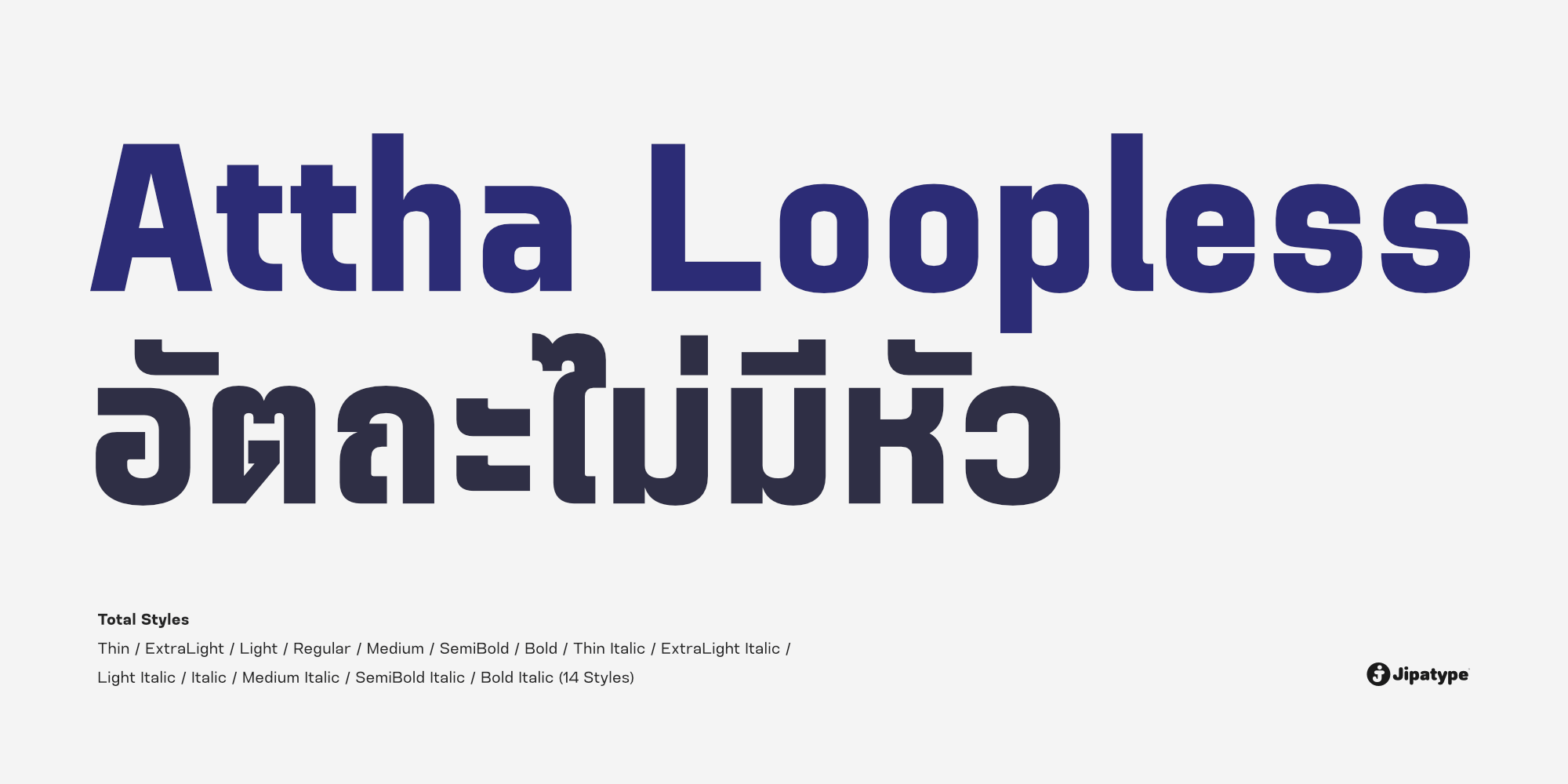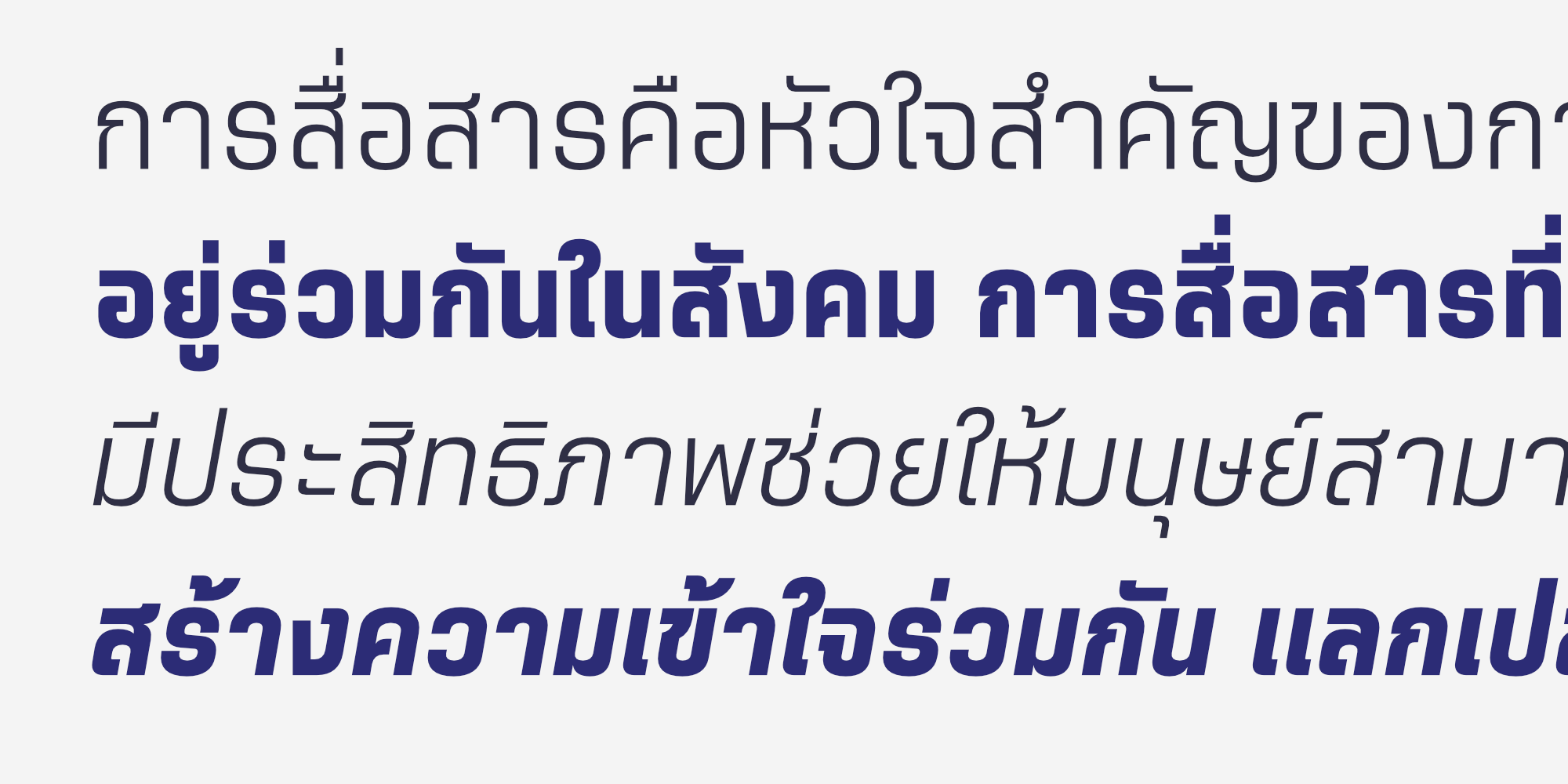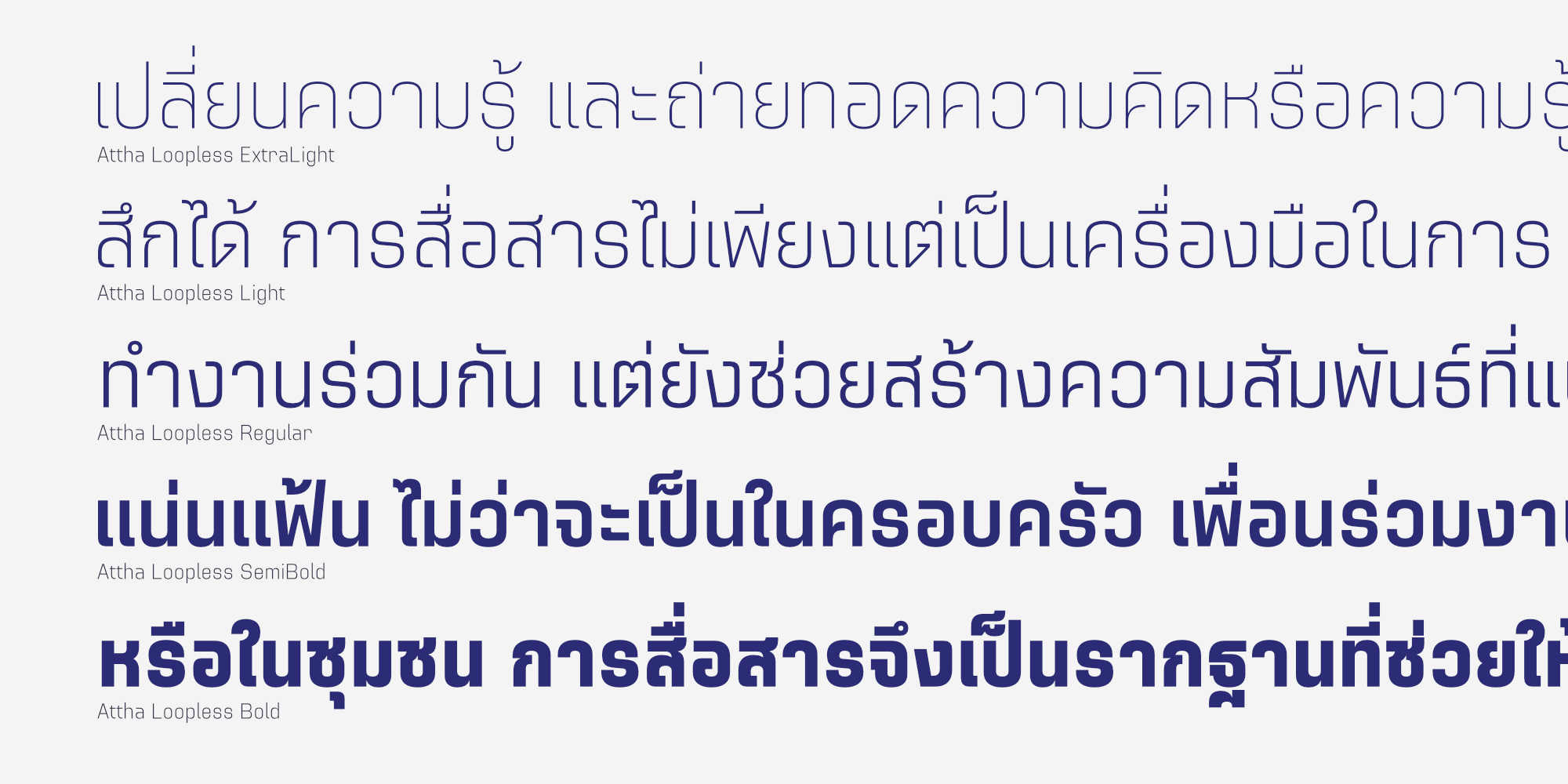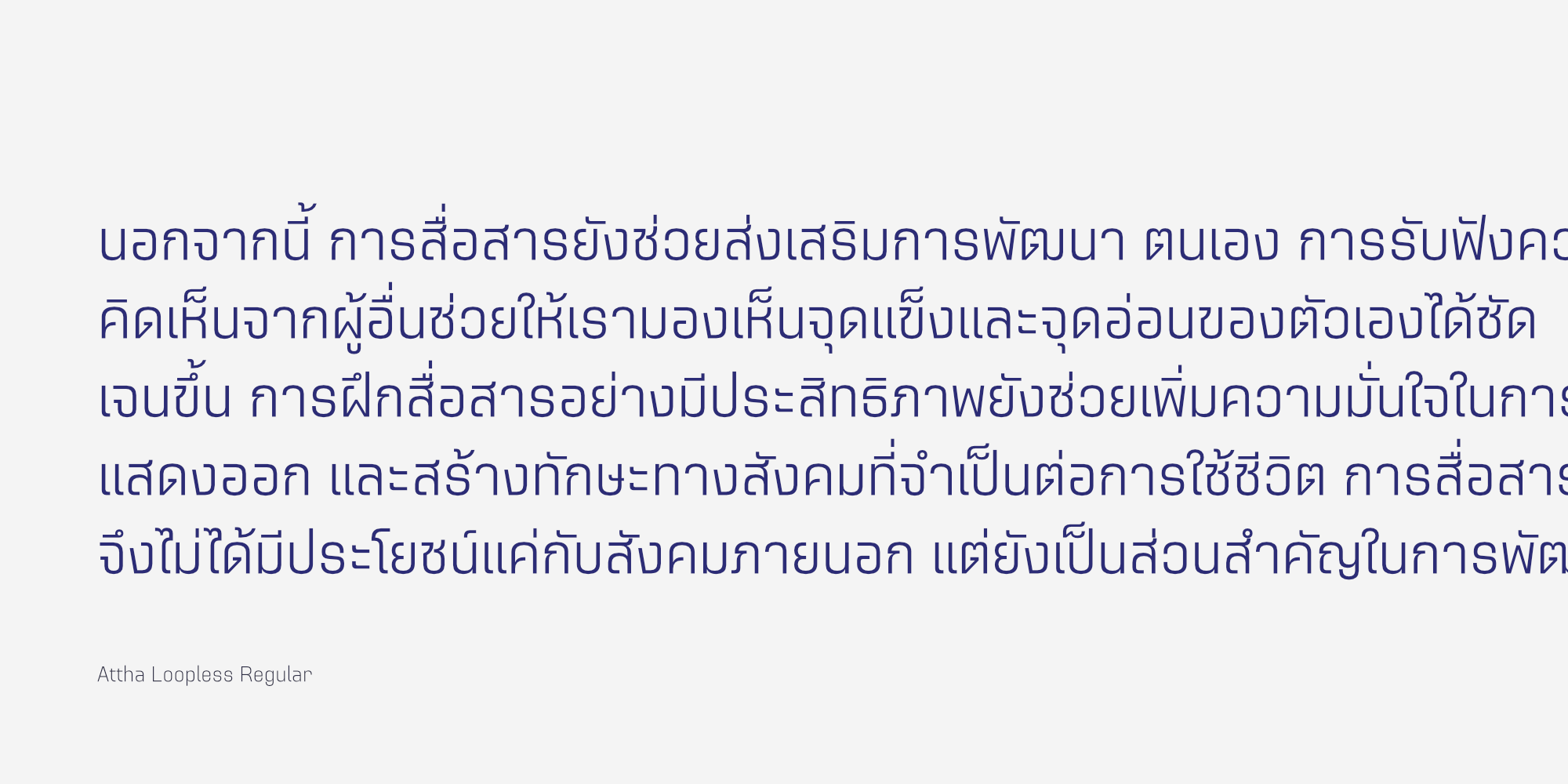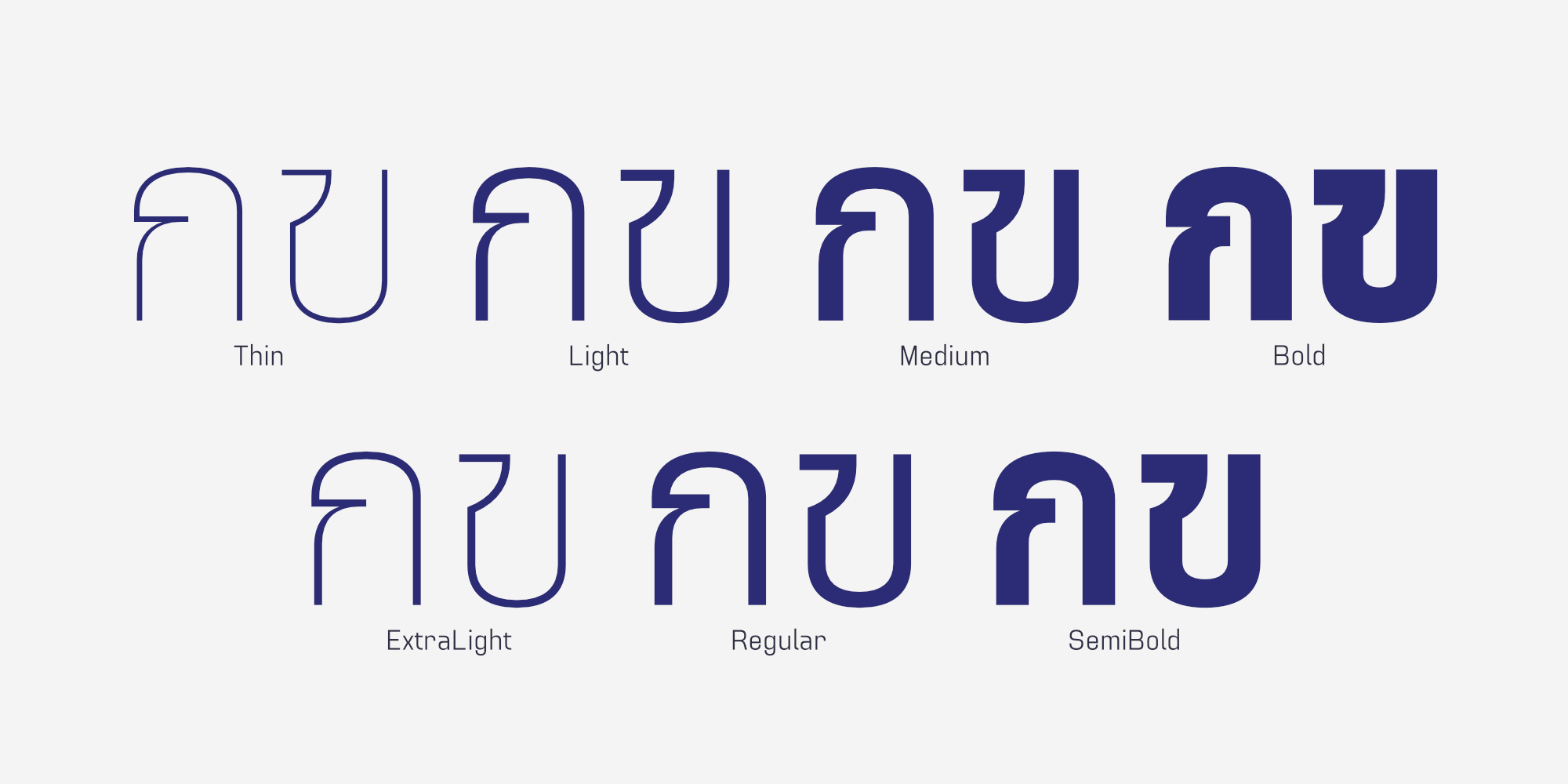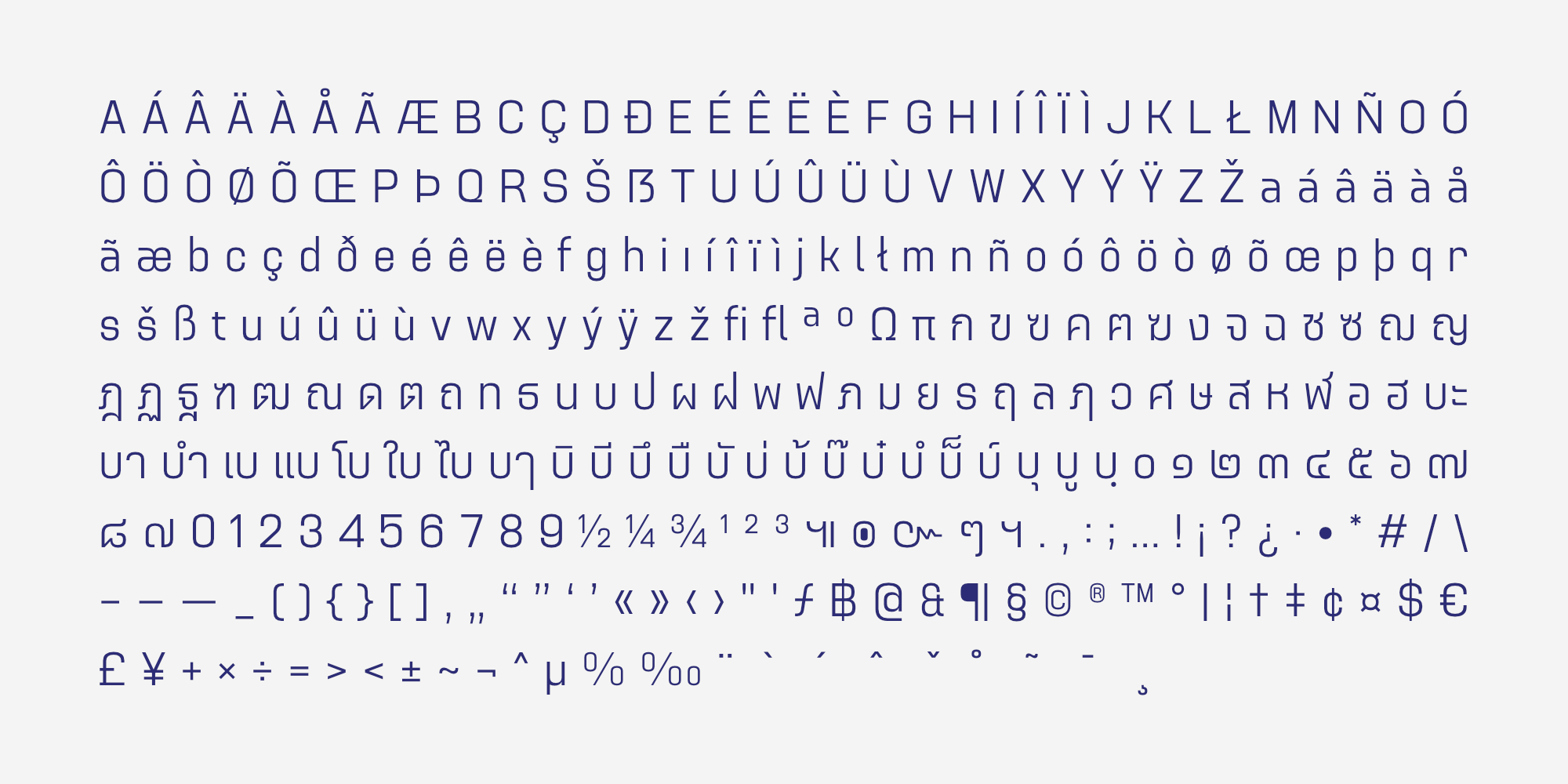
Attha Loopless เป็นชุดตัวอักษร Sans-serif สไตล์โมเดิร์นที่ถูกพัฒนาต่อยอดขึ้นจาก อัตถะ | Attha โดยปรับเปลี่ยนให้เป็นอักษรไทยแบบ “ไม่มีหัว” ทำให้มีรูปลักษณ์ที่โดดเด่นและเป็นสากลยิ่งขึ้น